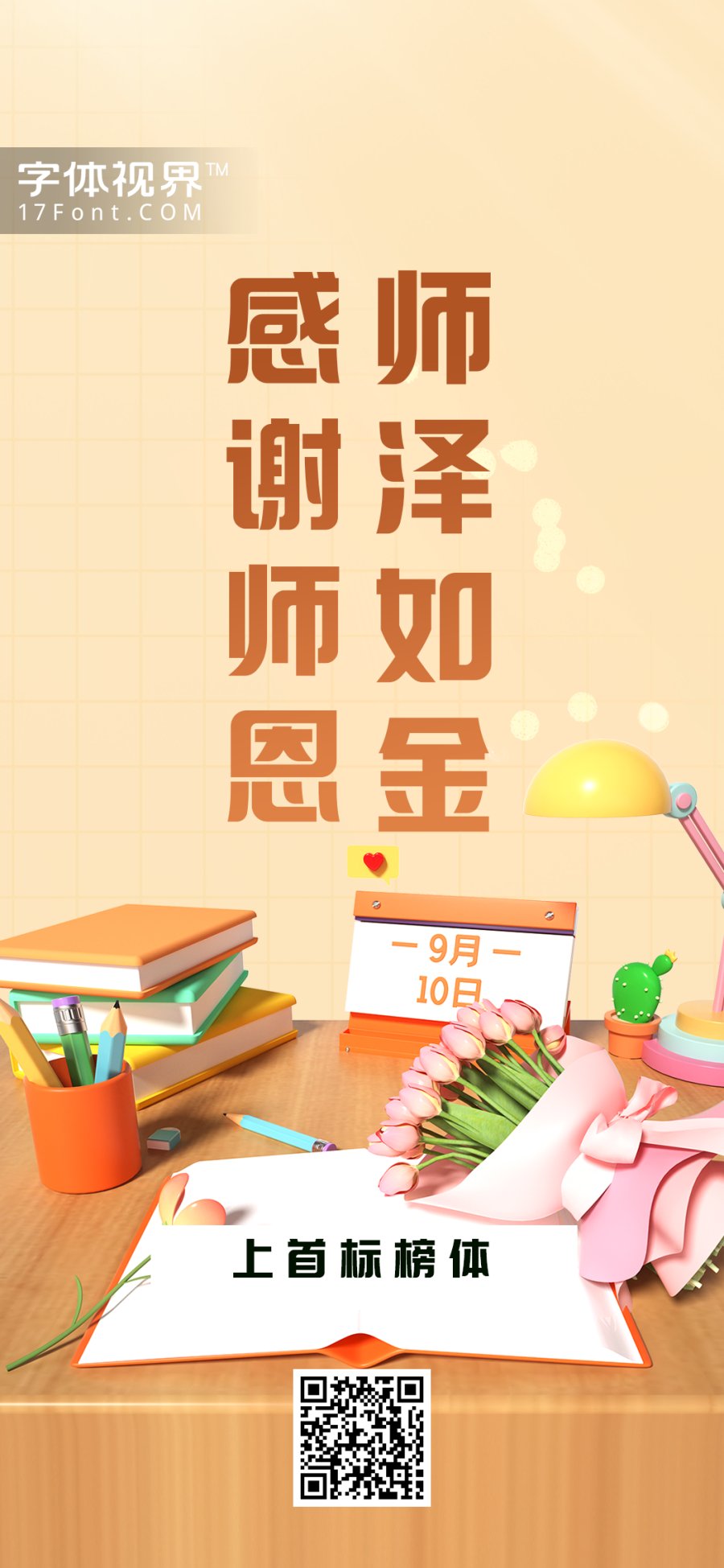
师恩重如山,今天我们用这款上首标榜体向我们的老师致以问候。
上首标榜体在字形上属于黑体类型,较宽的笔画赋予了它沉稳的风格,笔画转折处用完美弧线让字体多了一分灵巧,适用于搭配标志、广告标语、商业广告等高端属性。这是一款可商用的设计字体,如您需要在商用场合使用该字体,可在字体视界授权服务中心选择使用范围联系客服进行授权。
上首标榜体